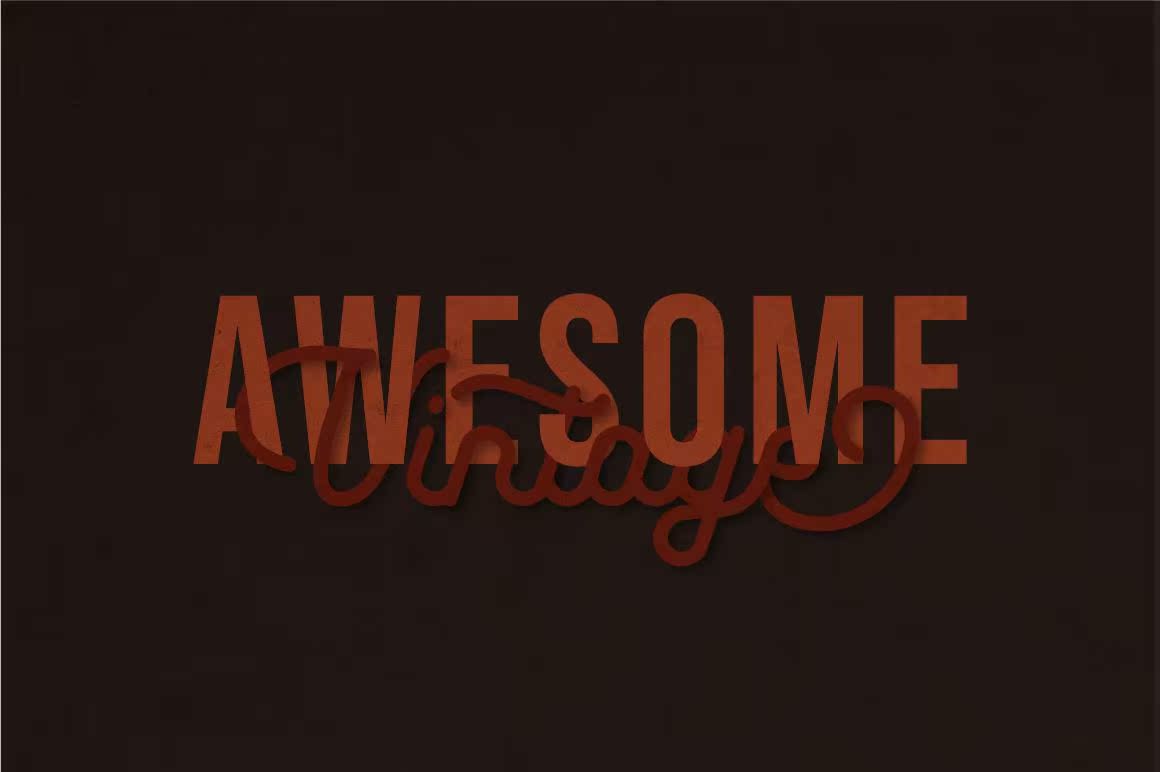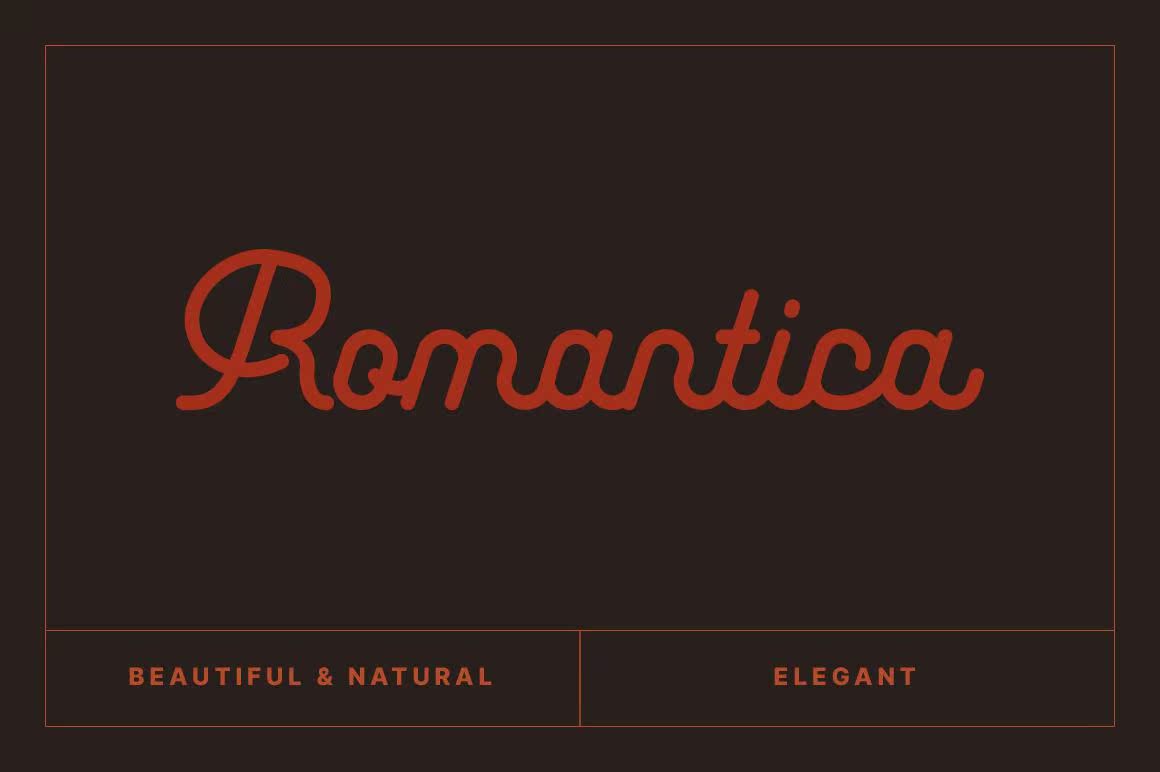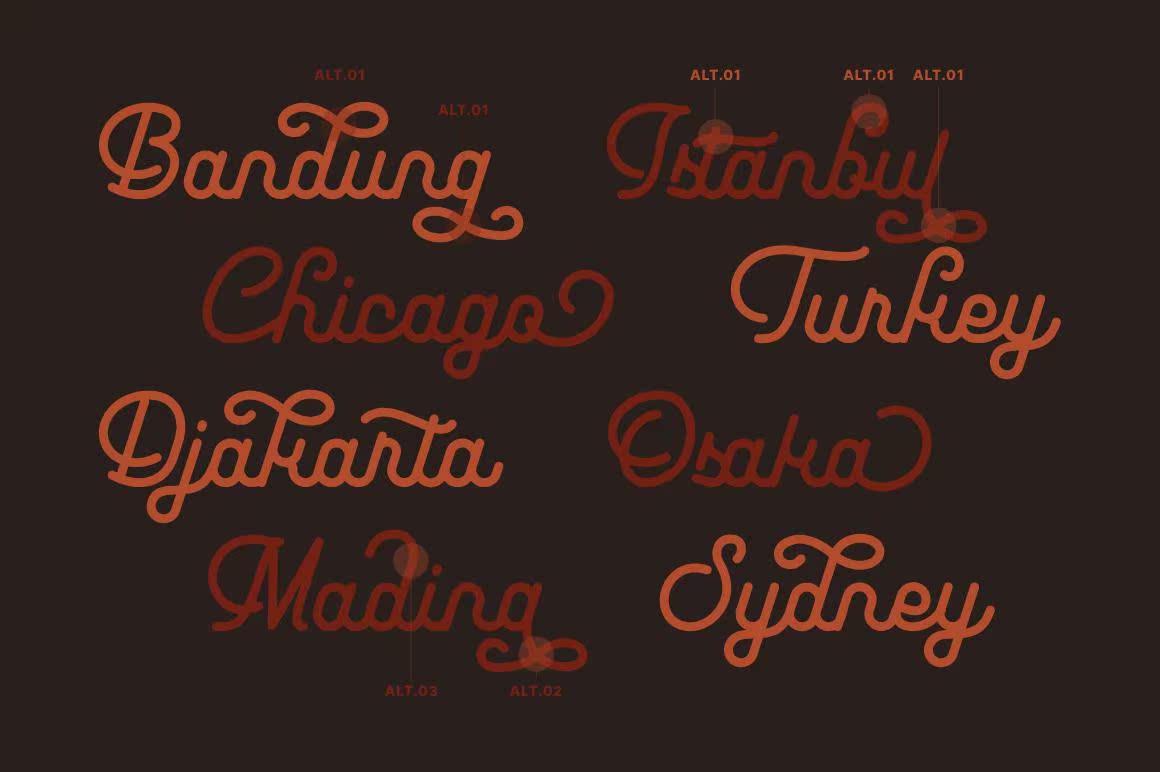
Leuthicklinescriptisabeautifulfulmonolinefont,完美的标志设计、品牌推广、服装设计、标牌、海报、婚礼宣传等等!我的目标是创建一个易于阅读的脚本字体,它将服务于各种各样的场景,并帮助您的项目保持完美和美丽。不要错过!别生气!Leuthicklinescriptisabeautifulfulmonolinefont,完美的标志设计、品牌推广、服装设计、标牌、海报、婚礼宣传等等!我的目标是创建一个易于阅读的脚本字体,它将服务于各种各样的场景,并帮助您的项目保持完美和美丽。不要错过!别生气!